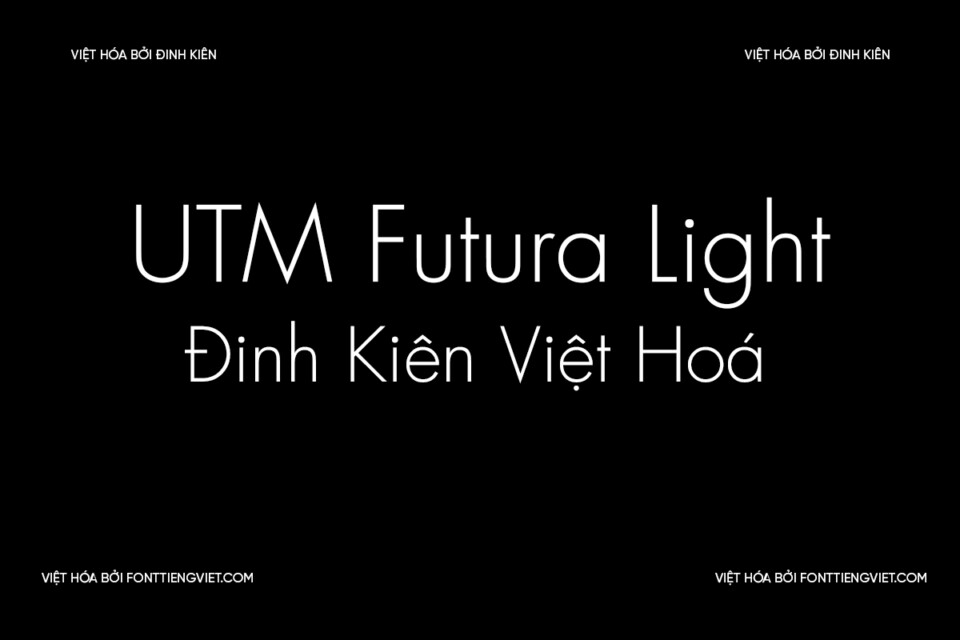
Trong thế giới đồ họa hiện đại, việc lựa chọn Font Chữ phù hợp đóng vai trò quyết định đến tính thẩm mỹ của sản phẩm. Font Việt hoá UTM Futura Light là một phiên bản đặc biệt thuộc bộ chữ UTM nổi tiếng, mang phong cách tối giản và thanh lịch. Với đường nét mảnh dẻ nhưng dứt khoát, bộ font này được các bạn học sinh và giáo viên ưa chuộng khi làm slide bài giảng hoặc báo cáo sáng tạo. Việc sử dụng font chữ đã qua chỉnh sửa tiếng Việt giúp loại bỏ hoàn toàn lỗi hiển thị dấu, mang lại sự chuyên nghiệp tối đa cho người dùng.
Ưu điểm nổi bật của Font Việt hoá UTM Futura Light
Thiết kế hình học chuẩn mực
Đặc điểm nhận dạng lớn nhất của Font Việt hoá UTM Futura Light chính là cấu trúc dựa trên các hình khối cơ bản như hình tròn và hình tam giác. Điều này giúp văn bản trở nên gọn gàng, dễ nhìn và không gây mỏi mắt khi đọc các đoạn nội dung dài. Trong môi trường học đường, kiểu chữ này hỗ trợ trình bày các đề án khoa học một cách khoa học và hiện đại hơn bao giờ hết.
Tính ứng dụng linh hoạt trong giáo dục
Dù là thiết kế bìa sách, làm infographic hay soạn thảo văn bản hành chính, bộ font này luôn giữ được sự tinh tế. Sự nhẹ nhàng của biến thể “Light” tạo cảm giác thân thiện, phù hợp để trình bày những thông tin cần sự trang nhã. Bạn có thể dễ dàng cài đặt font trên các phần mềm phổ biến như Word, PowerPoint hay Photoshop để bắt đầu công việc sáng tạo của mình ngay lập tức.